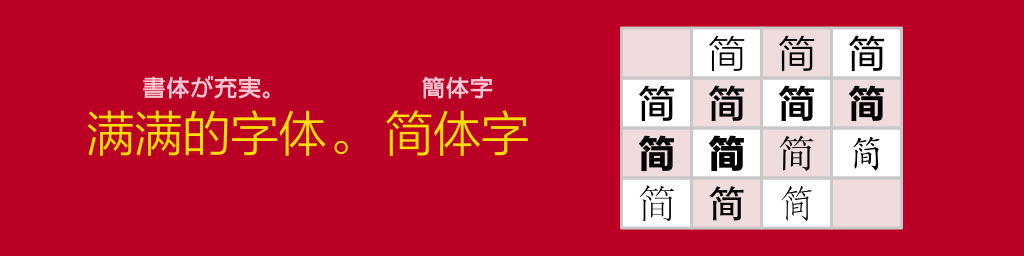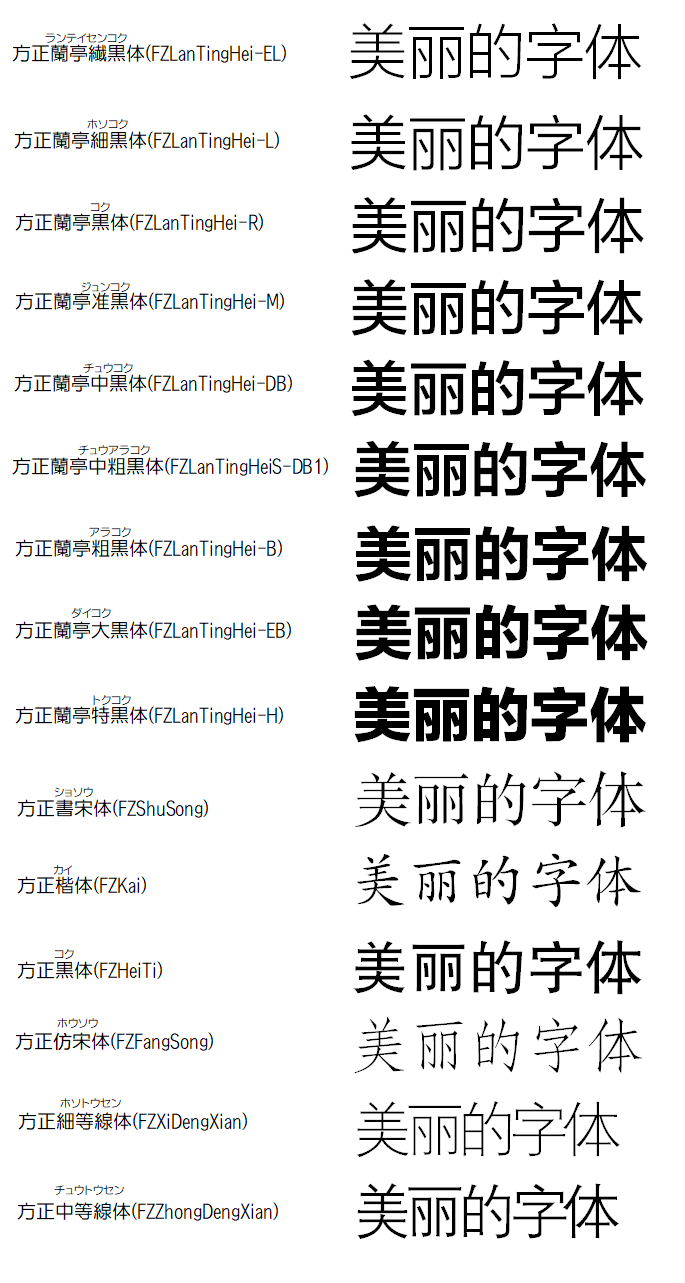
簡体字について
簡体字には4種類の書体があります。ご利用用途に合わせてお使いください。
Song           宋体(明朝系)
Hei              黒体(ゴシック系)
Fang Song  仿宋体(縦長の明朝体)
Kai              楷体(楷書体)
簡体字の特徴
方正蘭亭黒体(ホウセイ ランテイ コクタイ)
• 字面が大きく、文字と余白のバランスが良い美しいゴシック体です。
• ウェイト(フォントの画線の太さ)の種類が豊富です。
• 組込み用途(携帯電話、車載など)で中国や日本、韓国でも広く採用されています。
方正書宋体(ホウセイ ショソウタイ)
• すっきりとした見た目の書体です。
• 長く読んでも疲れにくく印刷に適しています。
• 現地の雑誌や書籍の本文、見出しなどで広く親しまれてきた書体です。
方正楷体(ホウセイ カイタイ)
• 均整が取れた構成と柔和で滑らかな筆遣い、縦横線の太さの変化が少ない筆文字です。
• 現地の新聞雑誌や書籍の本文、教科書などで最も良く使われております。
方正黒体(ホウセイ コクタイ)
• 文字の両端がラッパ口になっているのが特徴的です。
• ゴシック体でありながら明朝体の雰囲気も持ち合わせた中性的な書体です。
• 印刷媒体用途のほかにも画面表示などにも適しております。
方正仿宋体(ホウセイ ホウソウタイ)
• 文字の身を狭く、筆画を細く固くし、縦横線の字画の太さが揃っている書体です。
• くっきりとした美しいデザインは文字の識別もしやすく、設計図や書籍の引用文等に適しております。
方正等線体(ホウセイ トウセンタイ)
• 素朴ながら端正な字形で可読性も高く、黒体のデザインをルーツとした伝統的な風格の書体です。
• 印刷媒体の表題や本文、画面表示に適しております。